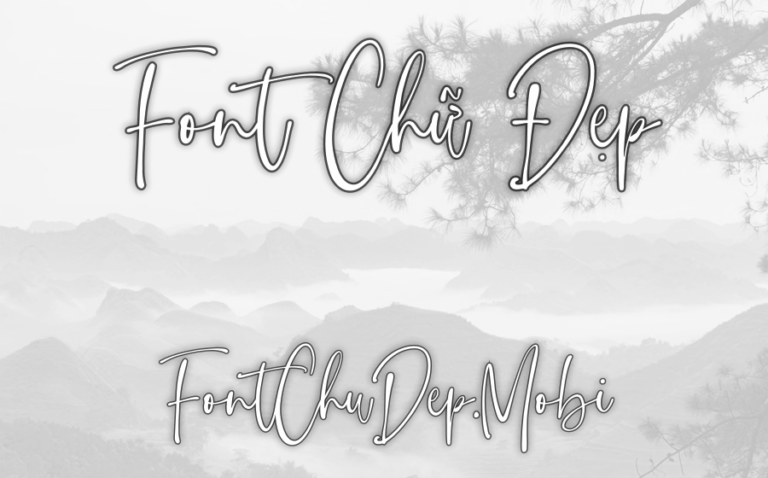
Sunlight Script là một font chữ viết tay tuyệt đẹp, được tạo ra bởi Typehill, đã để lại ấn tượng mạnh mẽ trong lòng những ai đam mê thiết kế. Với phong cách thư pháp hiện đại, Sunlight Script nổi bật nhờ các ký tự trang trí tinh tế và đường cơ sở uyển chuyển, mang đến sự mềm mại, linh hoạt như những dòng chữ đang di chuyển. Đặc biệt, phiên bản HN Sunlight Script đã được chuyên gia Huy Nam Việt hóa, cung cấp đầy đủ hỗ trợ cho các ký tự tiếng Việt, cho phép người dùng tại Việt Nam dễ dàng tích hợp vào các dự án thiết kế, từ đó đáp ứng nhu cầu sáng tạo của cộng đồng.
Nói về các đặc điểm thiết kế, Sunlight Script toát ra vẻ đẹp tự nhiên của một nét chữ viết tay uyển chuyển. Đây là font chữ lý tưởng cho nhiều ứng dụng từ thiệp mời, tiêu đề, bao bì sản phẩm đến các dự án sáng tạo khác. Sự thân thiện và gần gũi của nó khiến Sunlight Script trở thành lựa chọn tuyệt vời cho các thiết kế như áp phích giáo dục, bài báo tạp chí và những ý tưởng liên quan đến thương hiệu. Đặc biệt, ngành giáo dục, ẩm thực, thiệp cưới và các lĩnh vực đòi hỏi sự sáng tạo và cảm giác gần gũi sẽ tìm thấy một người bạn đồng hành hoàn hảo trong Sunlight Script. Sự linh hoạt cùng nét tinh tế của font chữ này cho phép nó dễ dàng thích nghi với nhiều phong cách, từ truyền thống đến hiện đại, mang lại sự mới mẻ và khác biệt cho mọi dự án thiết kế.